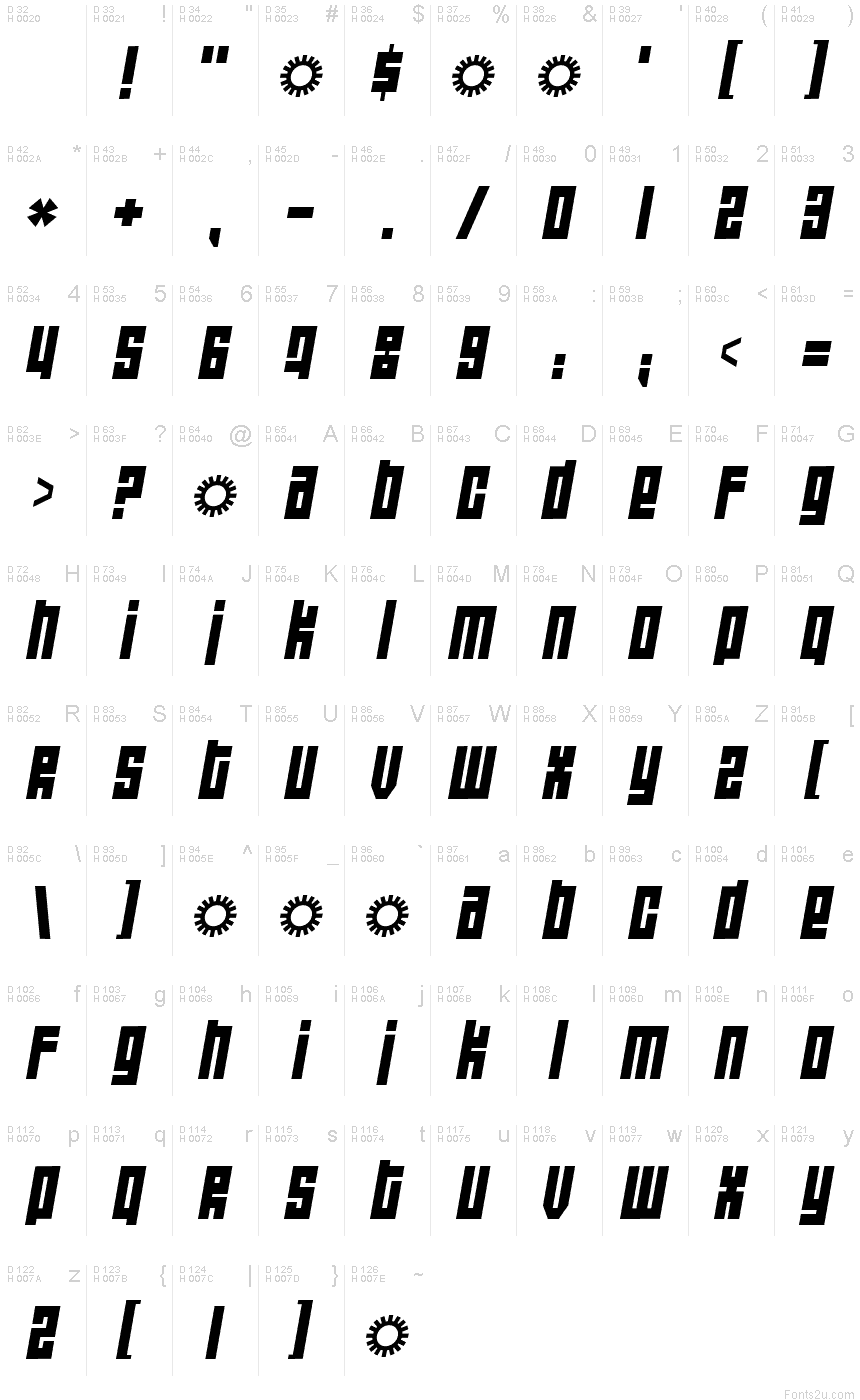
Wide awake Black
Wide Awake Black autorstwa Jakoba Fischera to darmowy, techniczny font typu display z elektronicznym pulsem, przypominającym zarwaną noc. Litery zbudowane są z wysokich, sztywnych kresek, przełamanych ostrymi, poziomymi cięciami, dzięki czemu cały krój przypomina migający wyświetlacz lub szybki szkic miejskich świateł – z odpowiednią dawką nieregularności, by nie stać się sterylnym.
Sprawdza się na muzycznych ulotkach, w menu gier, nagłówkach plakatów, wizerunkach klubów i planszach tytułowych, gdzie kompaktowy, futurystyczny rytm jest ważniejszy niż gładkość. Jako darmowy font, nadaje się również do tekstów na okładki, promocji aplikacji i krótkich znaków graficznych, ponieważ te pocięte formy tworzą dynamikę i napięcie, nawet przy użyciu zaledwie kilku liter.